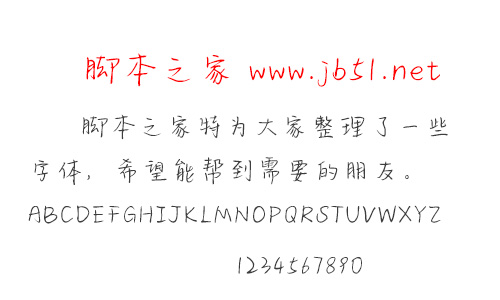
字心坊袁茵體是字心坊推出的一款硬筆手寫藝術(shù)字體,字跡深沉有力,運筆細膩不失流暢,格局端方而嚴(yán)謹,適應(yīng)于報紙和雜志和書籍中常用字體, 海報、個性促進品牌標(biāo)志設(shè)計、字體設(shè)計等領(lǐng)域,歡迎喜歡字心坊袁茵體的朋友前來現(xiàn)在使用。